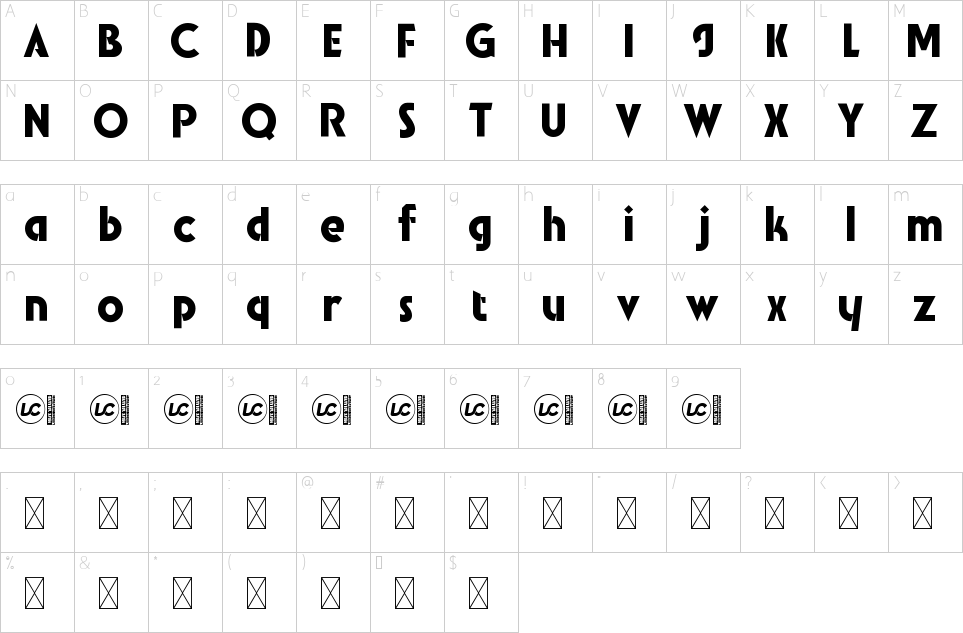
A Johor Font é uma fonte elegante e sofisticada disponível gratuitamente tanto para Windows quanto para Mac. Desenvolvida pela Lettercorner Studio, esta fonte está sendo baixada mais de 1.183 vezes. A Johor oferece uma variedade de opções de estilo que podem aprimorar o aspecto de qualquer projeto. Com uma aparência atraente e de alta qualidade, ela é ideal para designers que desejam adicionar um toque único a seus materiais. Seja em um layout de página, um site personalizado ou até mesmo em um projeto de impressão, Johor será uma escolha agradável. Download a Johor Font hoje e experimente a diferença que ela pode fazer em seus projetos de design.